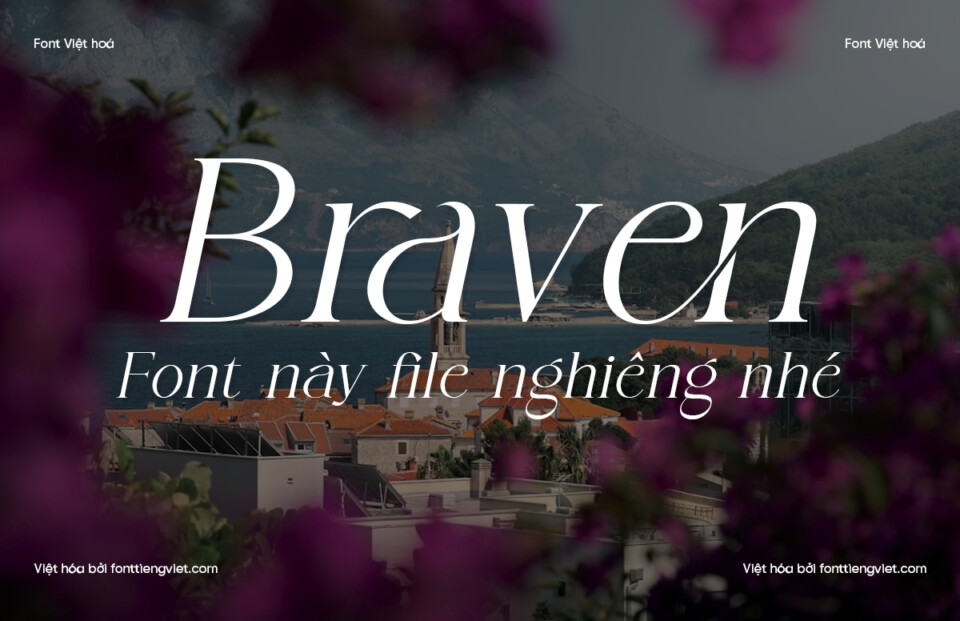
Font Việt hóa 1FTV VIP Braven Italic
Font Việt hóa 1FTV VIP Braven Italic – Bộ Font Serif Nghiêng Đẳng Cấp Cho Thiết Kế Chuyên Nghiệp
Trong thế giới sáng tạo đồ họa hiện đại, việc tìm kiếm một Font Miễn Phí chất lượng và hỗ trợ đầy đủ tiếng Việt luôn là ưu tiên hàng đầu của các nhà thiết kế. Một trong những lựa chọn nổi bật nhất trong thời gian gần đây chính là bộ Font Việt hóa 1FTV VIP Braven Italic. Đây là một phông chữ thuộc phong cách Serif (có chân) nhưng được tinh chỉnh với dáng nghiêng Italic vô cùng tinh tế, mang lại cảm giác vừa sang trọng, vừa linh hoạt. Đối với các bạn học sinh, sinh viên hay những người làm nội dung số tại Việt Nam, việc sở hữu Font Việt hóa 1FTV VIP Braven Italic sẽ giúp các sản phẩm trình chiếu và thiết kế trở nên ấn tượng và chuyên nghiệp hơn rất nhiều.
Đặc điểm nổi bật của Font Việt hóa 1FTV VIP Braven Italic
Bộ phông chữ này không chỉ đơn thuần là một kiểu chữ nghiêng thông thường. Điểm nhấn của Font Việt hóa 1FTV VIP Braven Italic nằm ở những đường nét thanh mảnh kết hợp với các góc bo tròn mềm mại nhưng vẫn giữ được sự dứt khoát của dòng Serif cổ điển. Khi sử dụng vào thực tế, bộ chữ này tạo ra một nhịp điệu hình ảnh rất lôi cuốn, dễ dàng thu hút ánh nhìn của người xem ngay từ những giây đầu tiên. Sự cân bằng giữa độ dày và độ mảnh của các nét chữ giúp nó giữ được độ hiển thị sắc nét trên cả màn hình điện thoại lẫn các bản in ấn vật lý.
Khả năng hiển thị và tính ứng dụng cao
Đúng như tên gọi “VIP”, Font Việt hóa 1FTV VIP Braven Italic được chăm chút kỹ lưỡng về hệ thống dấu tiếng Việt. Bạn sẽ không gặp phải tình trạng lỗi font hay các dấu câu bị lệch so với thân chữ như những bộ font chưa qua xử lý. Điều này đặc biệt quan trọng khi bạn thực hiện các dự án yêu cầu tính thẩm mỹ cao như thiết kế bìa sách, làm tiêu đề cho các tạp chí thời trang hoặc tạo nội dung trên mạng xã hội. Sự thanh thoát của dáng nghiêng còn giúp bộ font này trở thành công cụ đắc lực để nhấn mạnh những thông điệp quan trọng hoặc dùng làm trích dẫn trong các bài thuyết trình tại trường học.
Cách sử dụng Font Việt hóa 1FTV VIP Braven Italic hiệu quả nhất
Để phát huy tối đa vẻ đẹp của Font Việt hóa 1FTV VIP Braven Italic, người dùng nên kết hợp nó với những bộ font không chân (Sans Serif) đơn giản để tạo ra sự tương phản. Chẳng hạn, bạn có thể dùng phông chữ này cho phần tiêu đề lớn hoặc các cụm từ cần tạo điểm nhấn, trong khi phần nội dung văn bản dài nên dùng các kiểu chữ đứng để dễ đọc hơn. Ngoài ra, vì đây là kiểu chữ nghiêng có thiên hướng nghệ thuật, bạn hãy thử áp dụng các hiệu ứng màu sắc tối giản như đen, trắng hoặc vàng đồng để tôn lên sự sang trọng vốn có của bộ chữ này trong các thiết kế của mình.
Lý do nên lựa chọn font chữ được Việt hóa chuẩn
Việc sử dụng các bản font đã được Việt hóa chỉn chu như 1FTV VIP Braven Italic không chỉ giúp tiết kiệm thời gian chỉnh sửa mà còn đảm bảo tính nhất quán cho toàn bộ thiết kế. Đối với các bạn học sinh đang làm quen với thiết kế, việc tiếp cận với những nguồn tài nguyên chuẩn mực sẽ giúp nâng cao tư duy thẩm mỹ và hiểu rõ hơn về cách sắp xếp bố cục chữ (typography). Bộ font này chính là minh chứng cho việc kết hợp hài hòa giữa ngôn ngữ phương Tây và hệ thống dấu đặc trưng của tiếng Việt.
Kết luận về bộ phông chữ 1FTV VIP Braven Italic